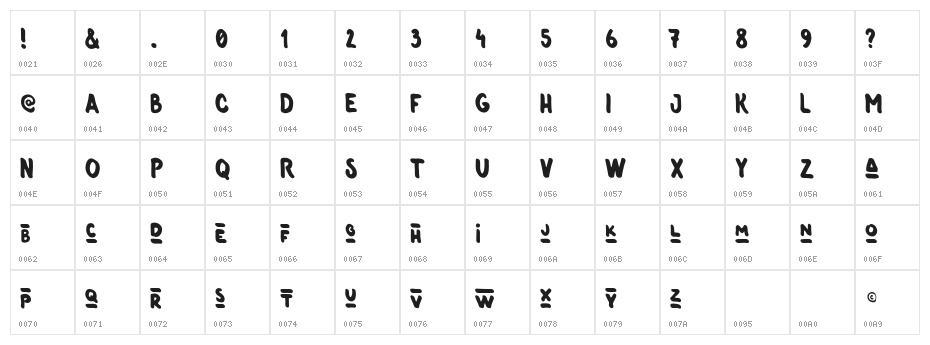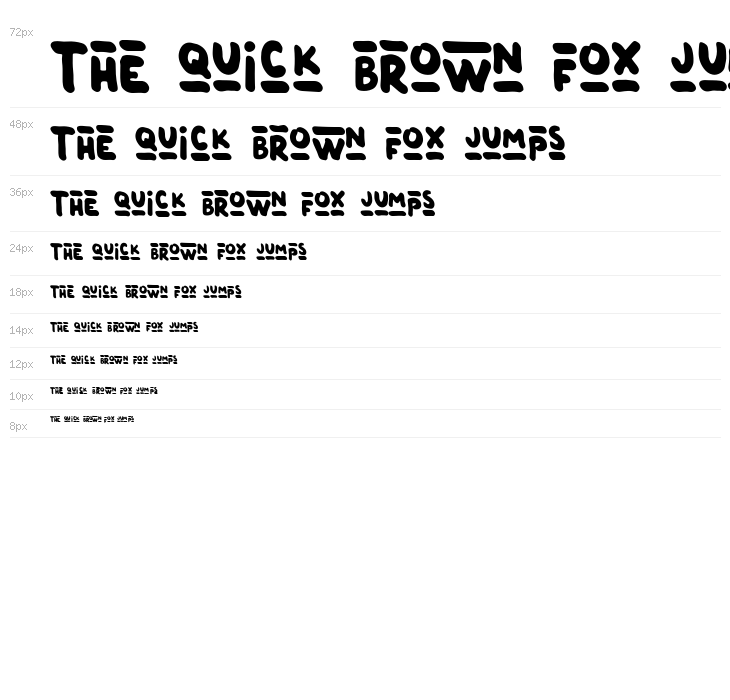
Oneer Font
| Stile generale | Playful, Whimsical |
| Progetti proposti | Ideal for children's books, playful branding, posters, and creative projects. |